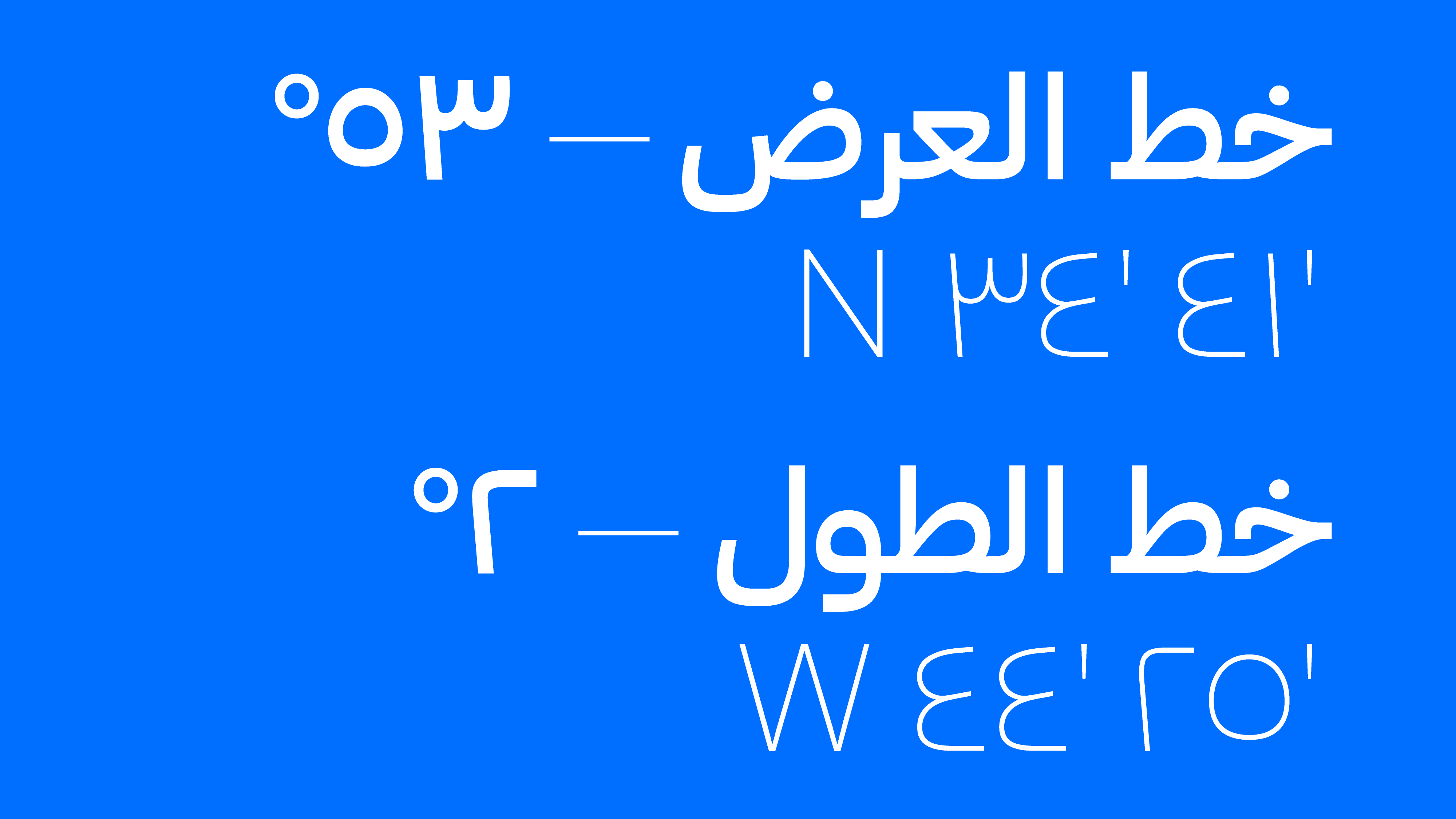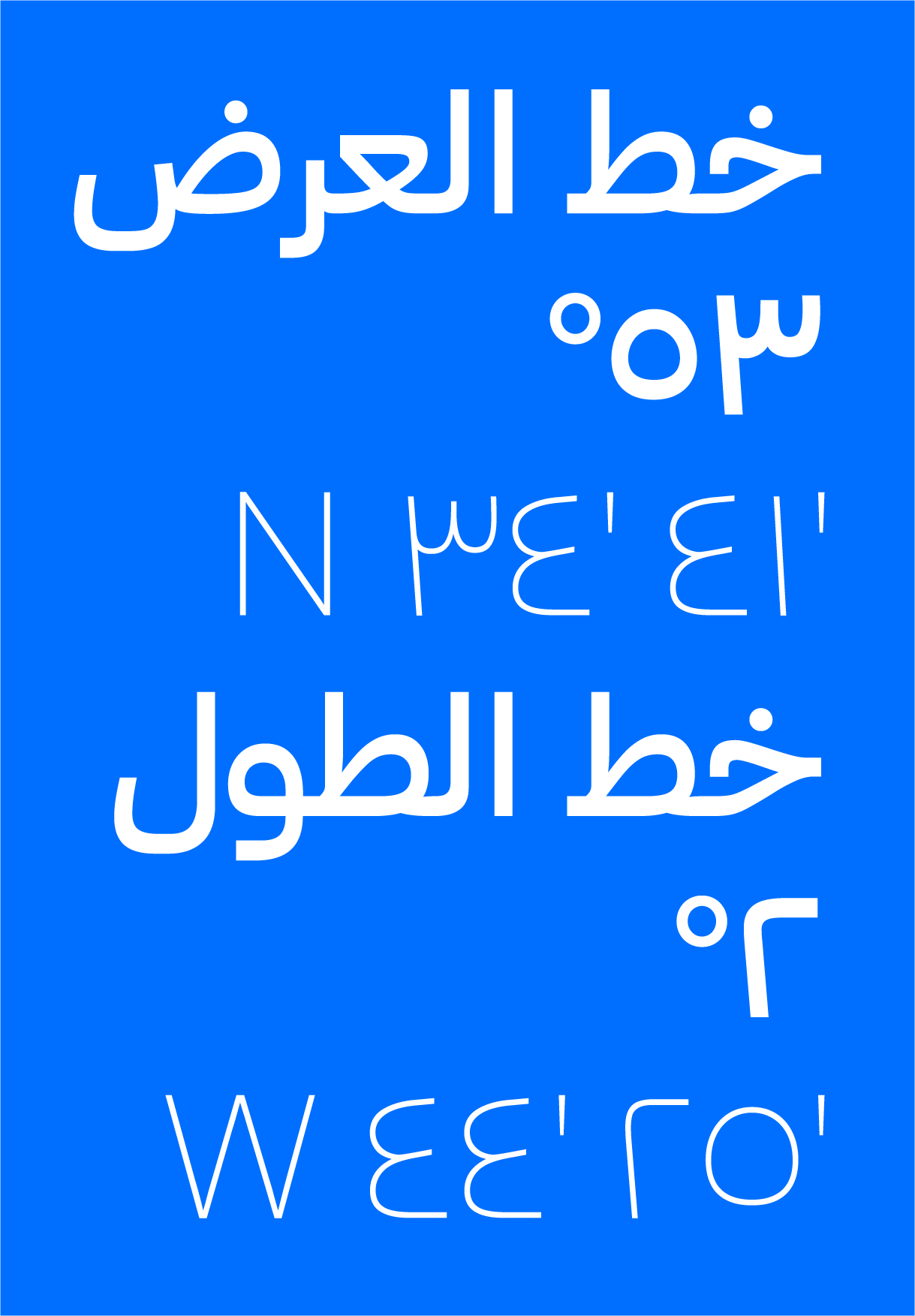
F37 Bolton Arabic Font Sampler
با روحیه‌ای آزمایشی و با هدف ایجاد چیزی کاملاً منحصر به فرد، ما یک خط مستقیم و افقی را به هر حرف وارد کردیم. حتی به حروفی که ذاتا گرد هستند.